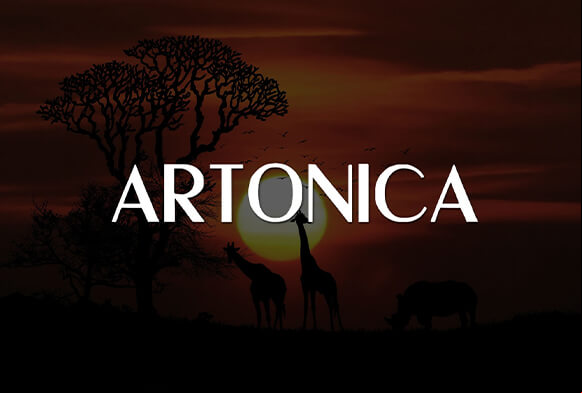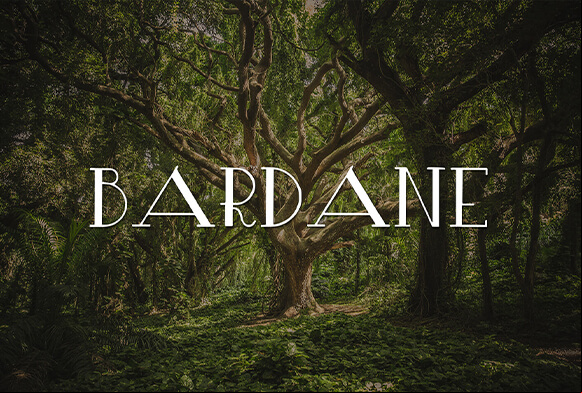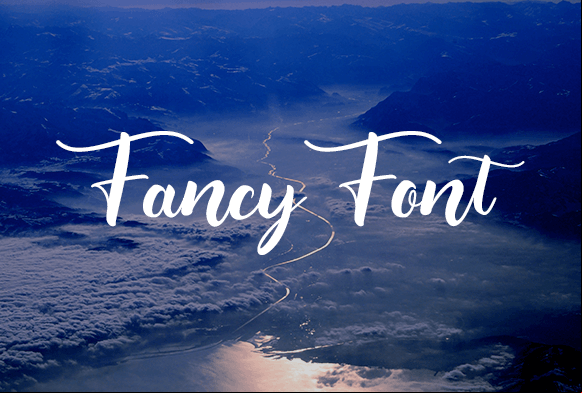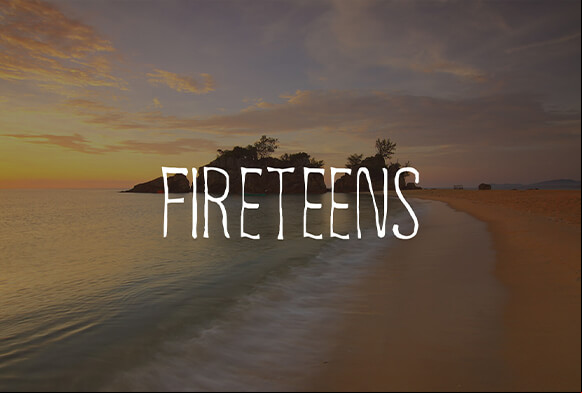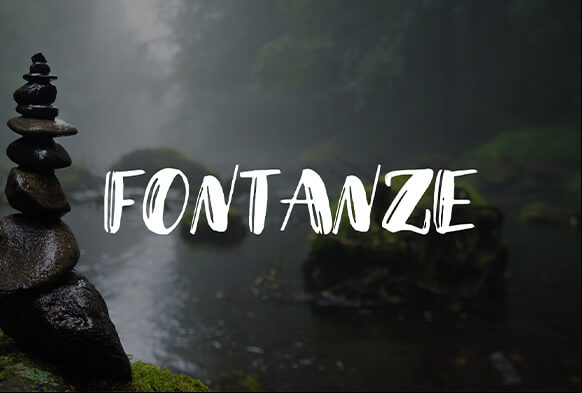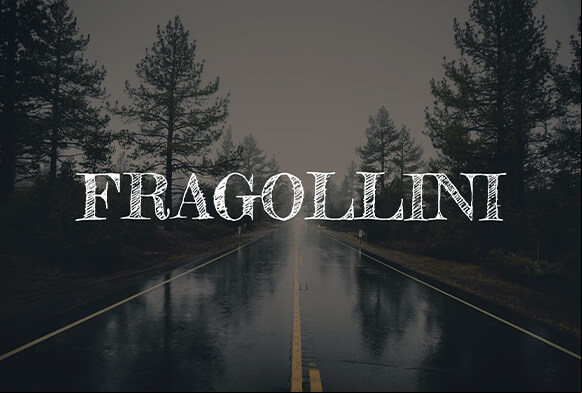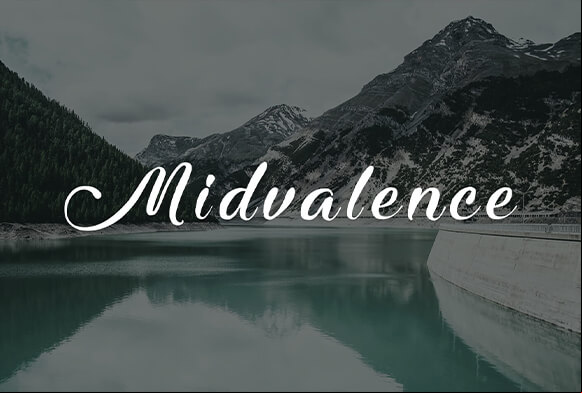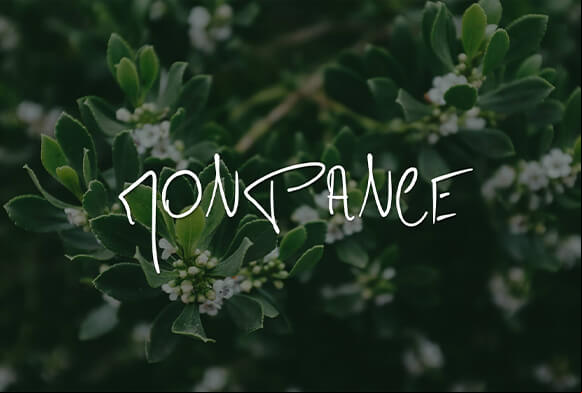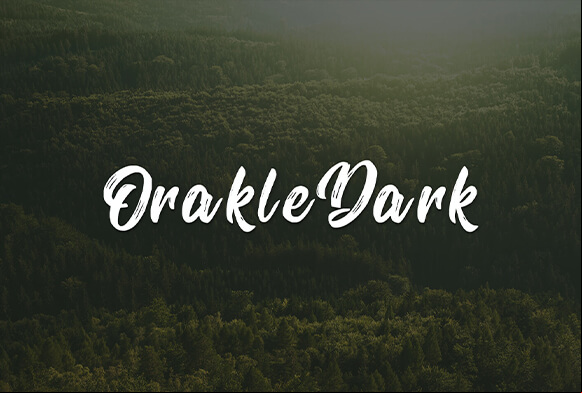
خطوط فوتوشوب مجانية 1x1n5f
إذا واجهت مهمة إضافة نص إلى التصوير الفوتوغرافي الخاص بك ، فإن خطوط Photoshop المجانية هذه المصممة بواسطة محترفي الصور المحترفين ستكون مفيدة للغاية بالنسبة لك. لا تضع في مقدمة صورتك الخط الأول الذي تصادفه ، ابحث عن خط رائع ينسجم بشكل متناغم مع أسلوب التصوير الخاص بك. من أجل راحتك ، اختار فريق FixThePhoto أفضل الخطوط المجانية لبرنامج Photoshop المناسبة لأنواع مختلفة من التصوير الفوتوغرافي. 1w3h1q
خطوط Photoshop # 1 "Acimetr" 3c3g5f
يتميز الخط بأحرف بسيطة وسهلة القراءة والتي ستكون مناسبة لأي صورة تنقل رسالة مهمة. تكتمل حواف الحروف بخطوط الرقيق للحصول على مظهر راقٍ.
الخطوط في Photoshop # 2 "Apogear" 48563t
إنه أفضل خط Photoshop يمكن تطبيقه إذا كنت تريد أن يبرز النص الخاص بك. فهو يجمع بين الخطوط السميكة والرفيعة والدوامات المستديرة.
خطوط فوتوشوب مجانية # 3 "Aquataken" 2u403j
خط واحد أكثر وضوحًا ، مع خطوط صغيرة إضافية على حواف الحروف. إنه خط تصوير عالمي يتناسب بالتأكيد مع أي صورة.
خطوط مجانية لـ Photoshop # 4 "Arcon" 4z1g1s
إنه أحد أفضل الخطوط الاحترافية التي تتميز بأحرف طويلة قليلاً. وبسبب بساطته ، فإنه يستخدم على نطاق واسع في الوسائط المطبوعة.
خط فوتوشوب رقم 5 "Artonica" 2340c
تعتبر واحدة من أعظم خطوط فوتوشوب المجانية المقروءة بالكامل لشعارات التصوير الفوتوغرافي. يمنح دمج الخطوط الرفيعة والسميكة والحواف الحادة والمستديرة مظهرًا مصقولًا للنص.
Photoshop Fonts Free # 6 "Fancy Fonts" 4k4312
هذا هو منشئ خطوط مجاني يسمح لك بتنسيق النص الخاص بك إلى خط أنيق مباشرة في متصفحك. تحتاج فقط إلى إدخال النص وتحديد الخط الذي تريده ونسخه
خط فوتوشوب مجاني # 7 "Bardane" 702n3s
إذا قمت بتطبيق هذا الخط على النص الخاص بك ، فسوف يلفت الأنظار بالتأكيد. مزيج غير عادي من الضربات الرفيعة والسميكة والدوامات المنحنية والخطوط العرضية الموجودة في الداخل أو فوق أو أسفل الحروف يمتزج مع أي خلفية صورة إبداعية.
خطوط فوتوشوب مجانية # 8 "Buke" e4g4r
إذا كنت بحاجة إلى لفت الانتباه إلى النص أو جعله أكثر وضوحًا ، فسيكون هذا الخط مثاليًا. تتميز بأحرف جريئة وسميكة مع ضربات منحنية تبدو جذابة للغاية.
خطوط Adobe Photoshop # 9 "Cardone" 4n6o1s
إنه ينتمي إلى قائمة أفضل الخطوط في Photoshop. يتم استخدام هذا الخط بشكل متكرر للنص الذي يعبر عن جميع أنواع المعلومات ، بسبب شكل الحرف المتسق والمظهر الأنيق.
خطوط فوتوشوب مجانية # 10 "Carridge" 3sm1n
إنها واحدة من أعظم أنماط خطوط Photoshop المجانية المرسومة يدويًا. ستعمل منحنياته وضرباته الفريدة بالتأكيد على تحديث أي نص أو عنوان.
خط لـ Photoshop # 11 "Chalsyn" 32682m
إنه محرف Serif ممتاز لأولئك الذين يبحثون عن خطوط شعار التصوير الفوتوغرافي. تتميز الحروف بخطوط رفيعة وبسيطة تساهم في إضفاء مظهر منعش على النص.
الخط فوتوشوب رقم 12 "Chitosa" 21166p
إنها واحدة من أكثر خطوط الفرشاة تميزًا في Photoshop. سيضيف مزيج الخطوط المعقدة والدوامات بعض الذوق إلى النص الخاص بك.
الخطوط فوتوشوب # 13 "Chusarky" t6g26
لا يمكنك أن تخطئ في هذا الخط الرقيق عندما تحتاج إلى أن يبدو النص بسيطًا وبسيطًا للغاية. ستتناسب الأحرف ذات السماكة المتوسطة مع الخطوط الواضحة في أي صورة.
خطوط PSD # 14 "Constanta" 5m11s
اسم هذا الخط يقول كل شيء - أحرف ذات شكل ثابت ، والتي تبدو غامقة بعض الشيء. يوصى باستخدام خط serif هذا للعناوين ، على سبيل المثال ، على مواقع الويب.
Photoshop Font Free # 15 "Contaria" 3v3l1a
إنه أحد الخطوط المجانية الأكثر ملاءمة لاستخدامها في لقطات الطبيعة والمناظر الطبيعية. تضفي حوافها الدائرية إحساسًا بالسلام والهدوء.
أفضل الخطوط في Photoshop # 16 "Dowlink" 52122j
يتم استكمال الحروف الهندسية الطويلة للخط بضربات فرشاة رفيعة وغير متساوية. قم بتطبيقه إذا كنت تريد تحقيق تأثير الجرونج من النص.
خط فوتوشوب رقم 17 " Eclipse" 5r3t1y
إذا كنت تبحث عن خطوط مجانية للمصممين ، فهي واحدة منهم. حواف مستديرة ولطيفة ، سوف يجذب التدوير المتنوع للأحرف الانتباه على الفور إلى الصورة والنص.
أفضل الخطوط في Photoshop # 18 "Enjoyinalos" 2g4x40
خط واحد آخر يبدو أنه تم رسمه بفرشاة. بسبب هذا التأثير ، تحتوي الحروف على مسافات فارغة لكنها لا تعقد قراءة الكلمات.
خط مجاني لـ Photoshop # 19 "Envatic" 1w4m1l
إنه أحد أبسط خطوط Photoshop المجانية وأكثرها وضوحًا. ستبدو الحروف الأنيقة والدقيقة رائعة في الصور العادية وأحادية اللون.
أفضل خطوط فوتوشوب رقم 20 "Epolos" 204c4y
يشار إليه على أنه أحد أكثر خطوط توقيع Photoshop أناقة. تبدو الأحرف ذات النقاط على الحواف والخطوط الطويلة المنحنية الجميلة وكأنها خط يدوي حقيقي من القرون السابقة.
أفضل الخطوط فوتوشوب # 21 "Fantartica" 3a6t6a
يمكن أن يكون هذا الخط بمثابة خط توقيع ممتاز. ستعمل الحروف المدمجة مع الدوامات الرائعة على تحسين أي صورة والنص الموجود فيها.